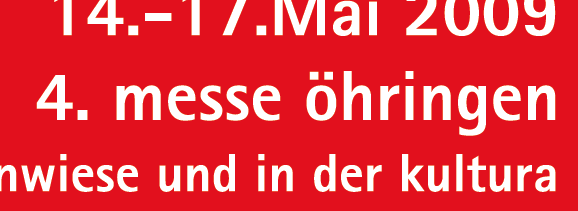
Ich komm einfach nicht drauf.
Passt!!! Juchu!
Objection, your Honor: die is doch fetter.
Die Extra Bold scheint mir recht genau zu passen.
Hast recht, es ist die extra bold.
Das habe ich dann noch selbst rausgefunden ;-)